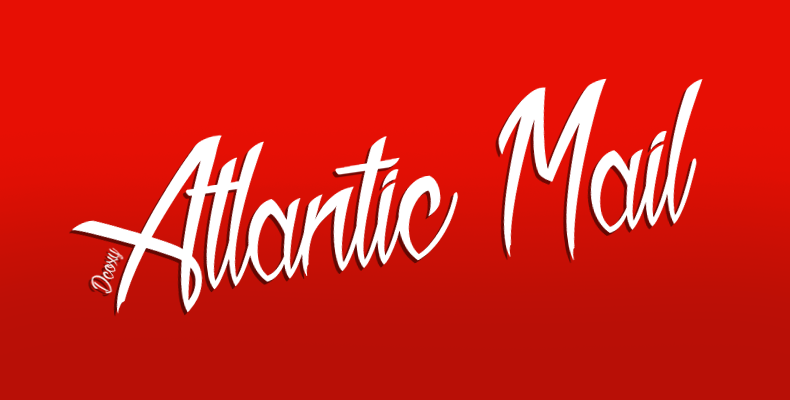
A Atlantic Mail Font é uma elegante escolha para designers que buscam personalidade embrenhada em simplicidade. Essa fonte tem uma vibe leve e descontraída, perfeita para projetos de design gráfico que precisam de um toque vivaz sem perder o respeito pelo trabalho serio. Ela foi criada por Hamilton, designer atento às nuances do design visual. As linhas finas e os espaçamentos justos refletem uma sofisticação moderna, perfeitamente adaptável para qualquer projeto em que você deseje dar um tom descontraído. Para uso comercial ou promocional, é fundamental ter a licença correspondente. Caso tenha interesse no produto, Hamilton pode ser contatado através do e-mail . É importante lembrar que sempre é uma boa prática verificar as condições de uso antes de usar qualquer fonte para projetos comerciais ou sem fins lucrativos. A Atlantic Mail Font não só adiciona um toque único a seus trabalhos, mas também ajuda a manter o respeito por direitos autorais em seu trabalho.